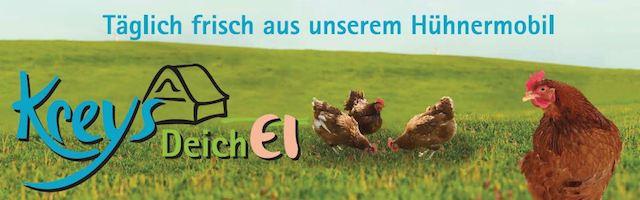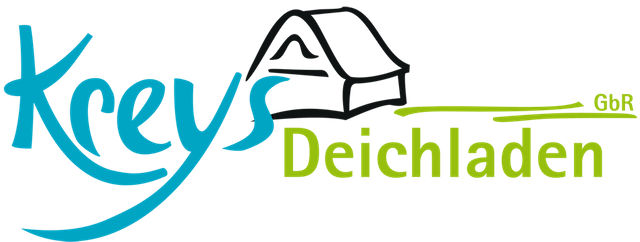
Suche Schrift von Kreys Deich Ei
Mehr Infos habe ich zu dem Logo leider nicht.
Doch, natürlich hast du die. Eine naheliegende: In welcher Schrift ist Kreys gesetzt? Solltest du bereits ausgeschlossen haben, dass EI nicht in derselben Schrift gesetzt wurde (oder auch einer Schrift aus derselben Familie), nimmt uns das viel Arbeit ab.
Da der Umgang mit Schrift dort insgesamt ziemlich freestyle ist, könnten die beiden Buchstaben zwar aus einer Schrift stammen, aber ebensogut auch, wie Ralf breits vermutet, schnell mit ein paar Pfaden gezeichnet sein. À propos Pfade: Es müsste da doch bestimmt eine Datei mit Pfaden vom Logo geben, denn man findet beim Googeln auch ein Foto von einer hauswandgroßen bedruckten Plane.